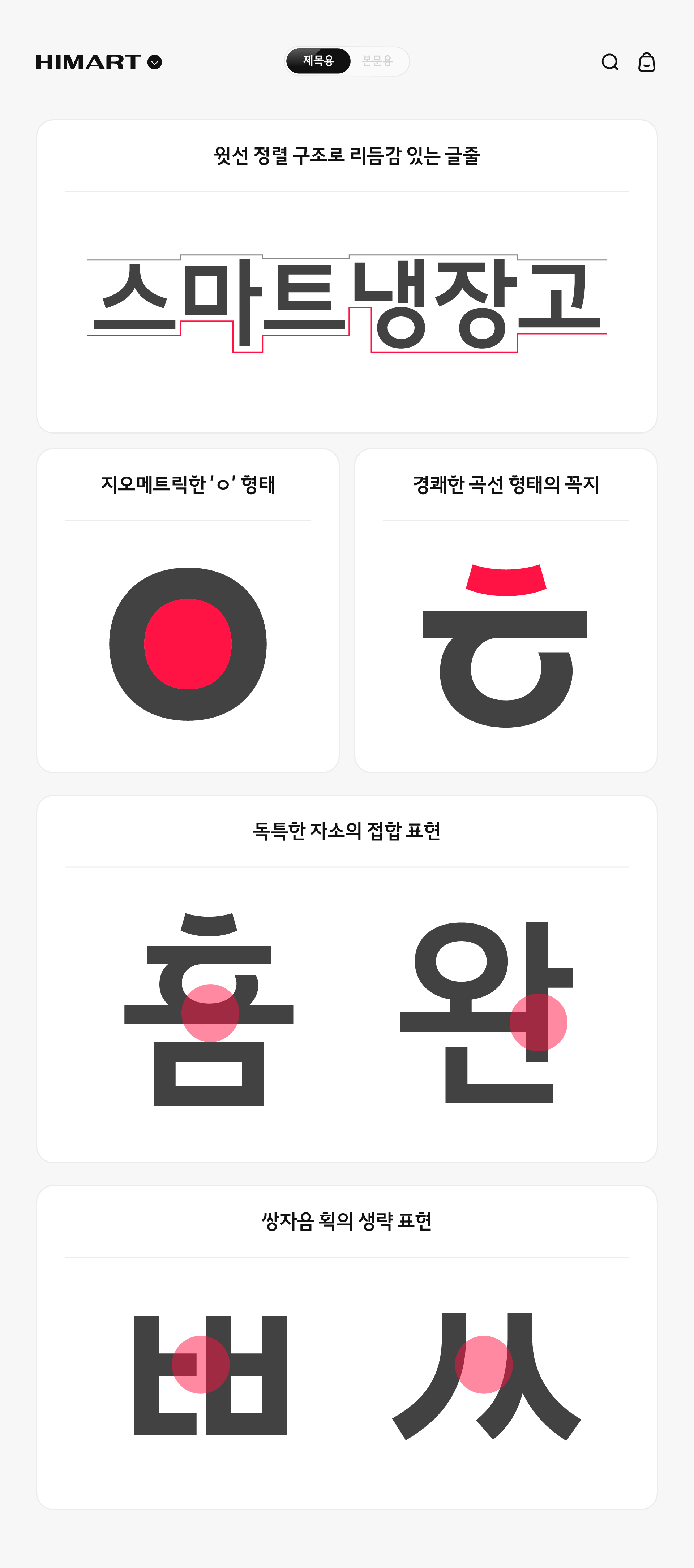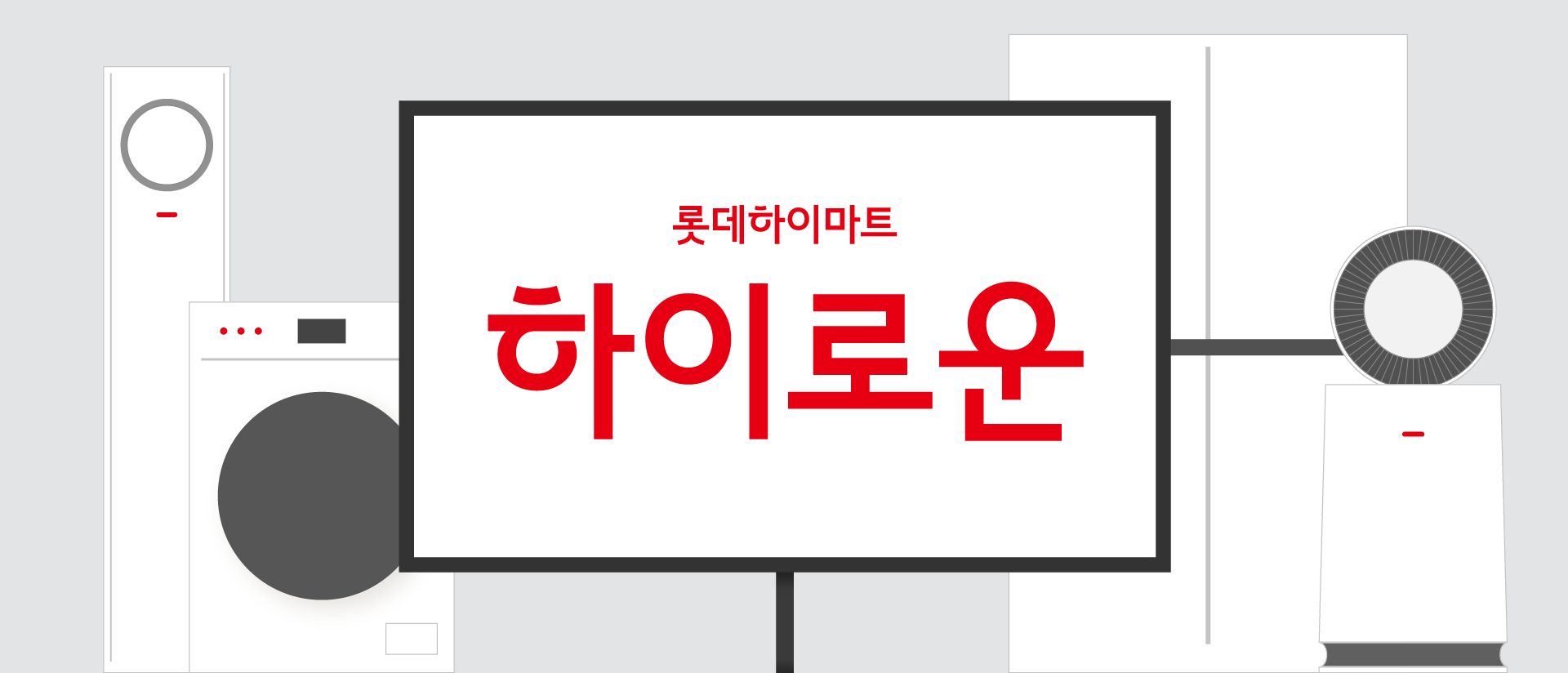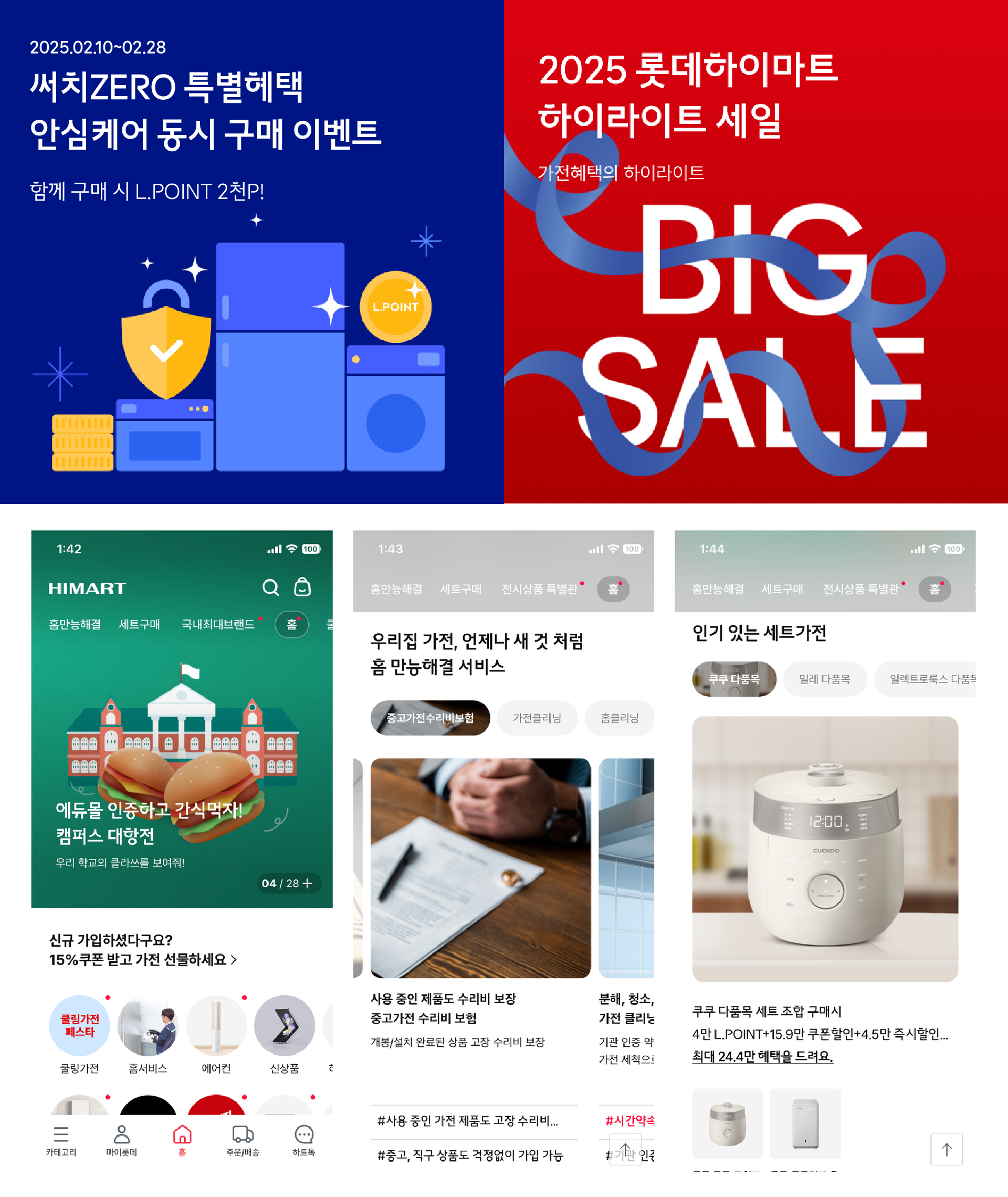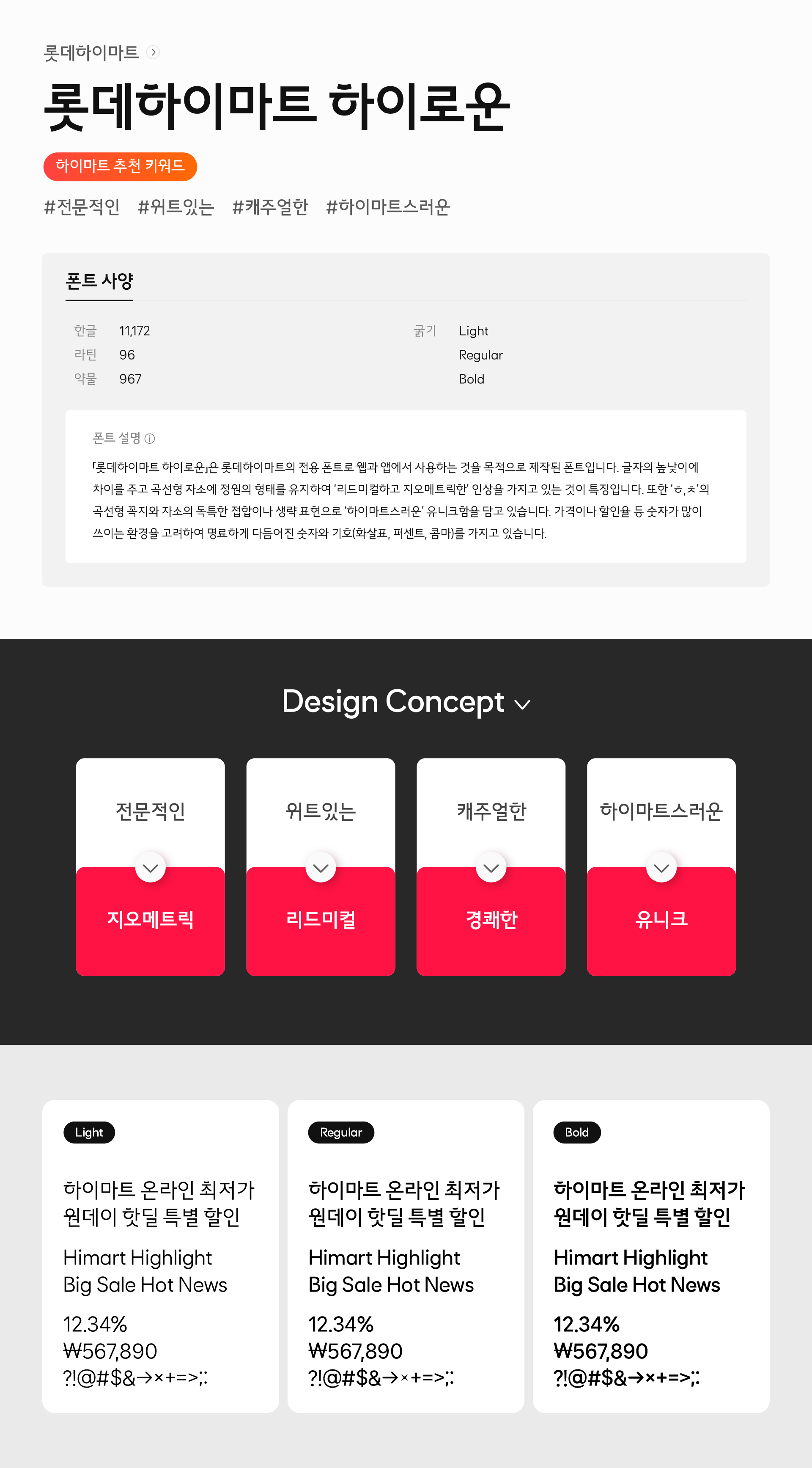
LOTTE HIMART
Hiroun
「롯데하이마트 하이로운」은 하이마트의 전용 폰트로 웹과 앱에서 사용하는 것을 목적으로 제작된 폰트입니다.
글자의 높낮이에 차이를 주고 곡선형 자소에 정원의 형태를 유지하여 ‘리드미컬하고 지오메트릭한’ 인상을 가지고 있는 것이 특징입니다. 또한 ‘ㅎ,ㅊ’의 곡선형 꼭지와 자소의 독특한 접합이나 생략 표현으로 ‘하이마트스러운’ 유니크함을 담고 있습니다.
가격이나 할인율 등 숫자가 많이 쓰이는 환경을 고려하여 명료하게 다듬어진 숫자와 기호(화살표, 퍼센트, 콤마)를 가지고 있습니다.
WeightLight, Regular, Bold
한글 11,172 / 라틴 96 / 약물 967